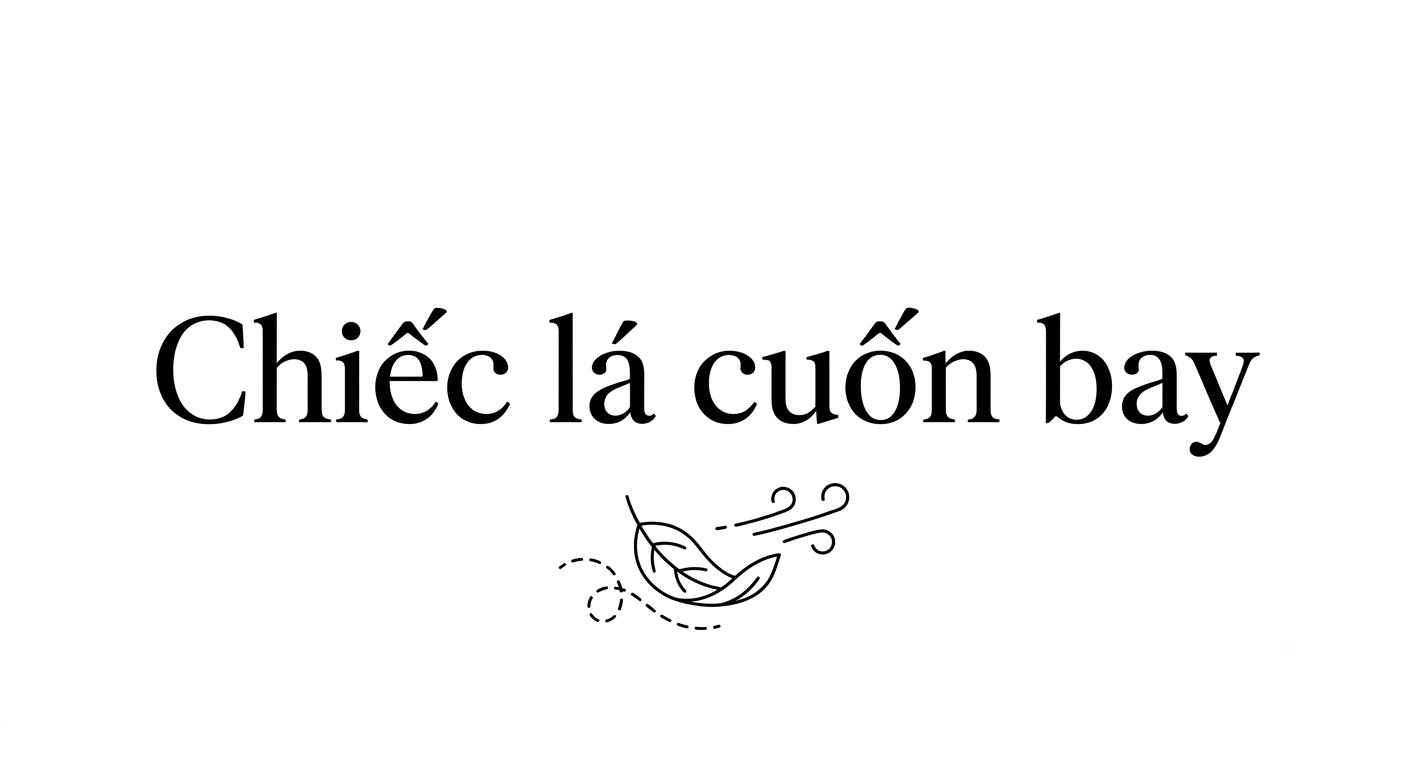
Nhiều nhà thiết kế khi sử dụng font Butler cho các dự án tiếng Việt thường gặp lỗi thiếu dấu, sai ký tự hoặc đường nét không giữ được độ sắc nét khi phóng lớn để in trên bao bì, hộp giấy và các ấn phẩm thương hiệu. Những vấn đề này có thể làm ảnh hưởng đến sự cân đối của bố cục, khiến thiết kế mất đi vẻ sang trọng đặc trưng của dòng font Serif cao cấp.
Font Butler là gì?
Font Butler là một bộ phông chữ thuộc dòng Serif (chữ có chân) hiện đại, được thiết kế bởi Fabian De Smet. Lấy cảm hứng từ sự kết hợp tinh tế giữa hai phông chữ kinh điển là Dala Floda và Bodoni, Butler mang trong mình vẻ đẹp của sự giao thoa giữa nét cổ điển và đương đại. Đặc trưng của bộ chữ này là cấu trúc vững chãi, đường chân chữ sắc sảo và độ tương phản nét thanh nét đậm được tính toán kỹ lưỡng. Điều này giúp Butler toát lên vẻ thanh lịch, quý phái nhưng vẫn rất dễ đọc, phù hợp cho nhiều mục đích trình bày khác nhau.
Hiện nay, bộ font này bao gồm 14 biến thể độ dày (Weights) từ Ultra Light đến Black, cùng với phiên bản Stencil độc đáo. Sự đa dạng này cho phép các designer linh hoạt trong việc phân cấp thông tin trên các ấn phẩm truyền thông hoặc bao bì sản phẩm. Bản Butler việt hóa mà In Viva chia sẻ đã được tinh chỉnh hệ thống dấu thanh và ký tự đặc biệt như “đ, ư, ơ” một cách cân đối, đảm bảo không bị lỗi “nhảy font” hay sai lệch kerning khi thiết kế nội dung tiếng Việt dài. Đây là công cụ đắc lực giúp nâng tầm thẩm mỹ cho các dự án quà tặng doanh nghiệp và thời trang cao cấp.
Lưu ý: Font Butler có các nét thanh khá mỏng ở những biến thể Light. Khi thiết kế in ấn trên chất liệu nhám hoặc vải canvas, bạn nên kiểm tra độ tương phản để nội dung không bị mờ do mực thấm sâu vào sớ giấy.
5 ứng dụng font Butler Việt hóa trong thiết kế và in ấn
Với phong cách Serif thanh lịch, kết hợp giữa nét chữ cổ điển và hiện đại, font Butler Việt hóa được ứng dụng phổ biến trong các dự án bao bì, nhận diện thương hiệu và quà tặng doanh nghiệp cao cấp:
• Thiết kế bao bì yến sào và mỹ phẩm cao cấp: Butler phù hợp để in tên thương hiệu trên hộp giấy Ivory, hộp cứng hoặc bao bì sản phẩm chăm sóc cá nhân. Các đường nét Serif giúp tạo cảm giác tinh tế, phù hợp với những thương hiệu theo đuổi phong cách sang trọng.
• Sản xuất bộ quà tặng văn phòng in logo: Logo hoặc tên doanh nghiệp sử dụng font Butler trên bút ký, sổ tay da, bình giữ nhiệt hoặc phụ kiện kim loại giúp sản phẩm có điểm nhấn riêng, phù hợp làm quà tặng tri ân đối tác.
• Thiết kế catalogue và ấn phẩm thời trang: Sự kết hợp giữa các phiên bản Butler Bold, Regular và Light giúp tạo sự phân cấp nội dung rõ ràng, phù hợp với catalogue, brochure hoặc hồ sơ giới thiệu thương hiệu.
• In thiệp mời và voucher doanh nghiệp: Những thông điệp ngắn bằng Butler trên giấy mỹ thuật giúp thiệp mời sự kiện, voucher hoặc thư cảm ơn thể hiện phong cách chỉn chu và tinh tế.
• In logo lên bộ ấm chén sứ quà tặng: Font Butler khi in nung trên men sứ tạo điểm nhấn cho các sản phẩm quà tặng đối ngoại, phù hợp với doanh nghiệp sử dụng trong các dịp gặp gỡ khách hàng, đối tác.
4 lưu ý kỹ thuật khi sử dụng font chữ Butler
Để font Butler giữ được vẻ đẹp đặc trưng khi ứng dụng vào sản xuất thực tế, designer cần chú ý:
• Kiểm soát độ dày nét chữ (Stroke): Butler có sự tương phản rõ giữa nét thanh và nét đậm. Khi in logo hoặc chữ kích thước nhỏ, nên lựa chọn biến thể phù hợp hoặc điều chỉnh độ dày nét để hạn chế tình trạng mất chi tiết trong quá trình in.
• Tối ưu đường Path cho gia công bế nổi: Khi sử dụng Butler cho logo dập nổi trên hộp quà, cần chuyển đổi font sang dạng vector và xử lý các điểm neo nhỏ. Điều này giúp các chi tiết Serif hiển thị rõ hơn trên giấy mỹ thuật hoặc carton lạnh.